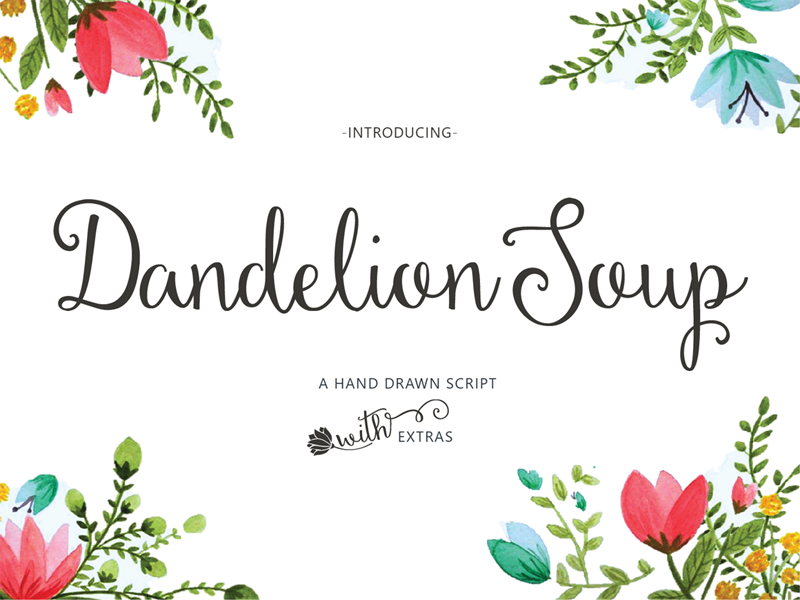
Dandelion Soup Script Font – Download Grátis
Dandelion Soup Script Font é uma nova tipografia script criada pela designer Emily Spadoni, oferecendo 180 diferentes caracteres desenhados a mão para diversos idiomas e dialetos. Este recurso não apenas ilustra o extenso alcance da fonte no que diz respeito à linguagem, mas também adiciona uma riqueza adicional com mais de 80 ornamentos feitos a mão, incluindo folhas e flores, bandejas, desenhos animados, chifres de palha e molduras. Ideal tanto para uso pessoal quanto comercial, esta fonte é perfeita para qualquer projeto que você deseje personalizar com elegância e detalhes únicos. Embarque nesta fonte única e veja como ela pode transformar seu design em algo extraordinário.